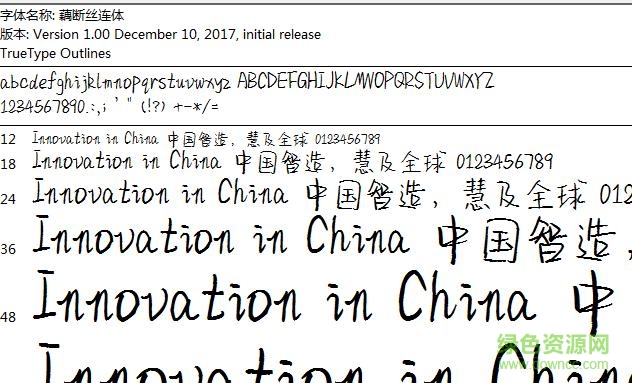
藕斷絲連體加粗版
藕斷絲連字體ttf是一款小清新類型的字體,這款字體被作者賦予了自然、隨性的特色,有喜歡這款字體的歡迎來綠色資源網(wǎng)免費下載使用!
藕斷絲連字體ttf簡介
藕斷絲連字體ttf是一款硬筆手寫字體,這款字體最大的特色的特色就是收筆的時候會有點連著,看上起非常的灑脫,長時間的欣賞也不會覺得乏!.